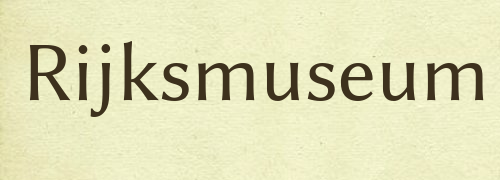
[Suche] Ähnliche Schriften wie...
Gute Frage – wenn hier etwas zusammenkommt sollte R::bert auf jeden Fall eine ›Alternativen zur Optima‹-Liste anlegen ...  :hammer:
Hehe, gute Idee! Is ja nich so, dass da noch kein Anlauf unternommen wurde: http://www.typografie.info/3/topic/26458-modernere-alternative-zur-optima/
In eine Liste von optimaartigen Schriften könnte auch die kostenlose Arsenal aufgenommen werden. Zwar hat die etwas strenger als die Optima wirkende und auch schmaler laufende Schrift nur die vier Standardschnitte, aber diese verfügen neben den lateinischen auch über kyrillische Zeichen sowie mehrere Opentype-Funktionen, wie Kapitälchen, eine Schwungschrift-Variante (nur Versalien), einen Stilistischen Satz mit alternativen a und g (leider als Satz 0 definiert  :neenee: ). Auch das große Eszett und sogar das ſ sind vorhanden.
Auch die von Gudrun Zapf-von Hesse geschaffen Christiana könnte in die Liste. Diese ist verspielter aber auch dynamischer als die Vorgabe von ihrem Mann. Leider ist die Lizenzierung der Christiana aber auch sündhaft teuer (Berthold).